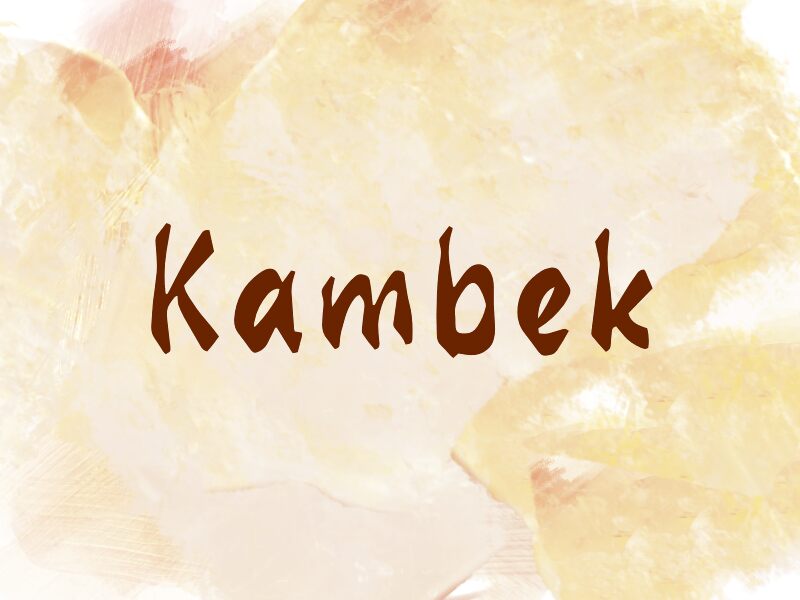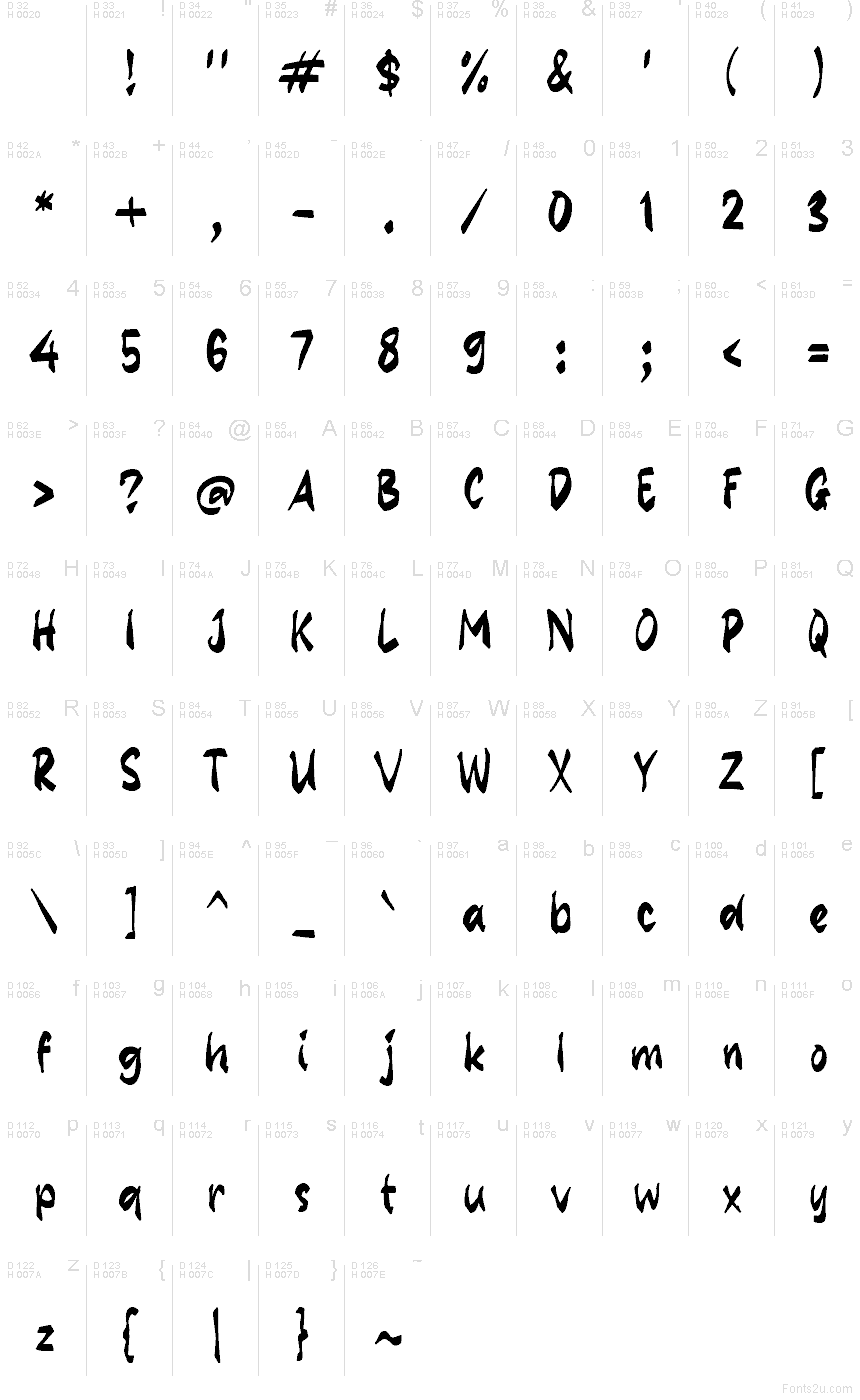
Kambek, créée par Wep, est une police manuscrite de style pinceau gratuite, au rythme libre et à la texture légèrement brute. Les lettres semblent tracées sur le vif, mêlant traits larges et appuyés à des pointes acérées, offrant au lettrage une énergie spontanée typique des affiches de rue.
Idéale pour les flyers de concerts, l'identité visuelle de cafés, les couvertures de fanzines, le packaging et les réseaux sociaux, c'est la police parfaite quand on cherche un rendu artisanal plutôt que trop lisse. Utilisez-la pour des titres courts, des génériques ou des logos : sa texture de pinceau irrégulière et son mouvement dynamique font tout le travail.
Kambek
Présentation et spécimen de la police Kambek
Table des caractères de la police Kambek
Table des caractères de Kambek : Latin de base, page 1
Glyphes de la police Kambek — Latin de base, page 1